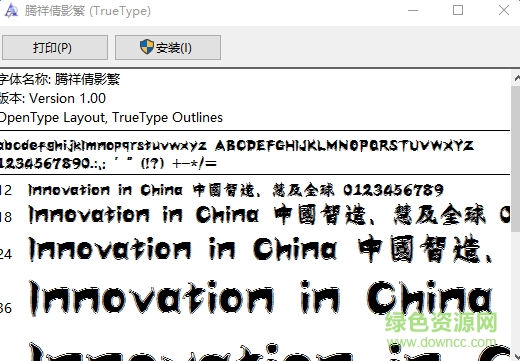
騰祥倩影繁是騰祥字庫(kù)中的一款繁體字體,還自帶描邊效果,因此寫出來(lái)的字是很好看的,而且這款字體實(shí)用性也很強(qiáng),可以用于很多方面,不管是書本印刷還是廣告設(shè)計(jì)都是可以的,歡迎大家來(lái)綠色資源網(wǎng)下載。
騰祥倩影繁字體雖是一款繁體字體,但是還是很實(shí)用的,寫出來(lái)的字效果也很好,大家可以用在很多方面,喜歡的朋友可以來(lái)綠色資源網(wǎng)下載。